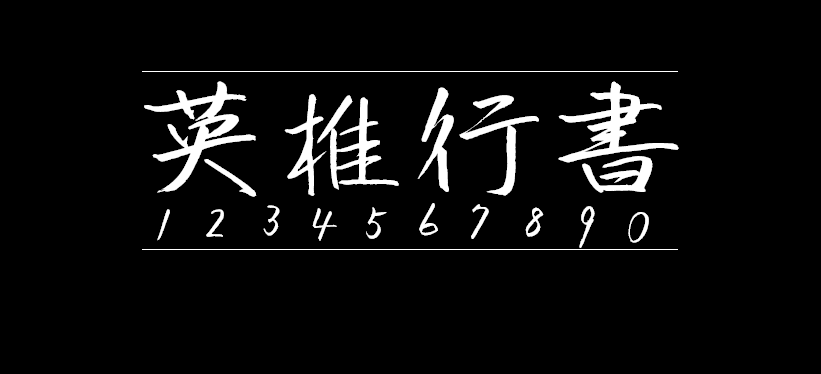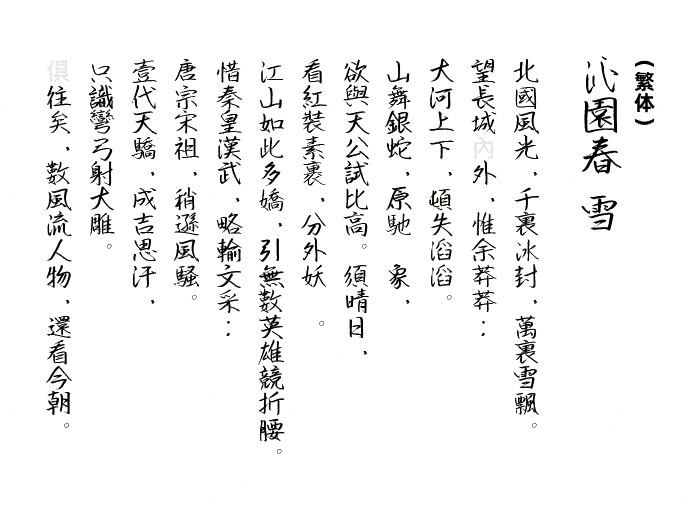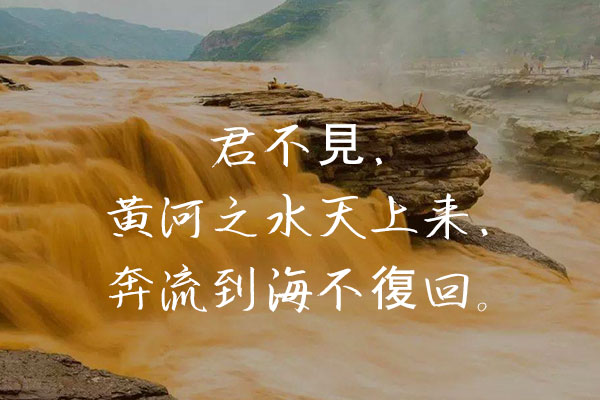
英椎行书
英椎行书(acgyosyo)也是日本acfont自己手写开发的一款字体,这款字体端庄雄伟,书写工整,是一款十分好看的手写字体。英椎行书共收录了6879个文字,因为日文字符一般是以JIS为标准,繁体字支持得相对比较完整,而简体字相对较少,喜欢的朋友赶紧下载吧!作者已经公开声明这款字体可以免费商用,所以大家放心使用吧!